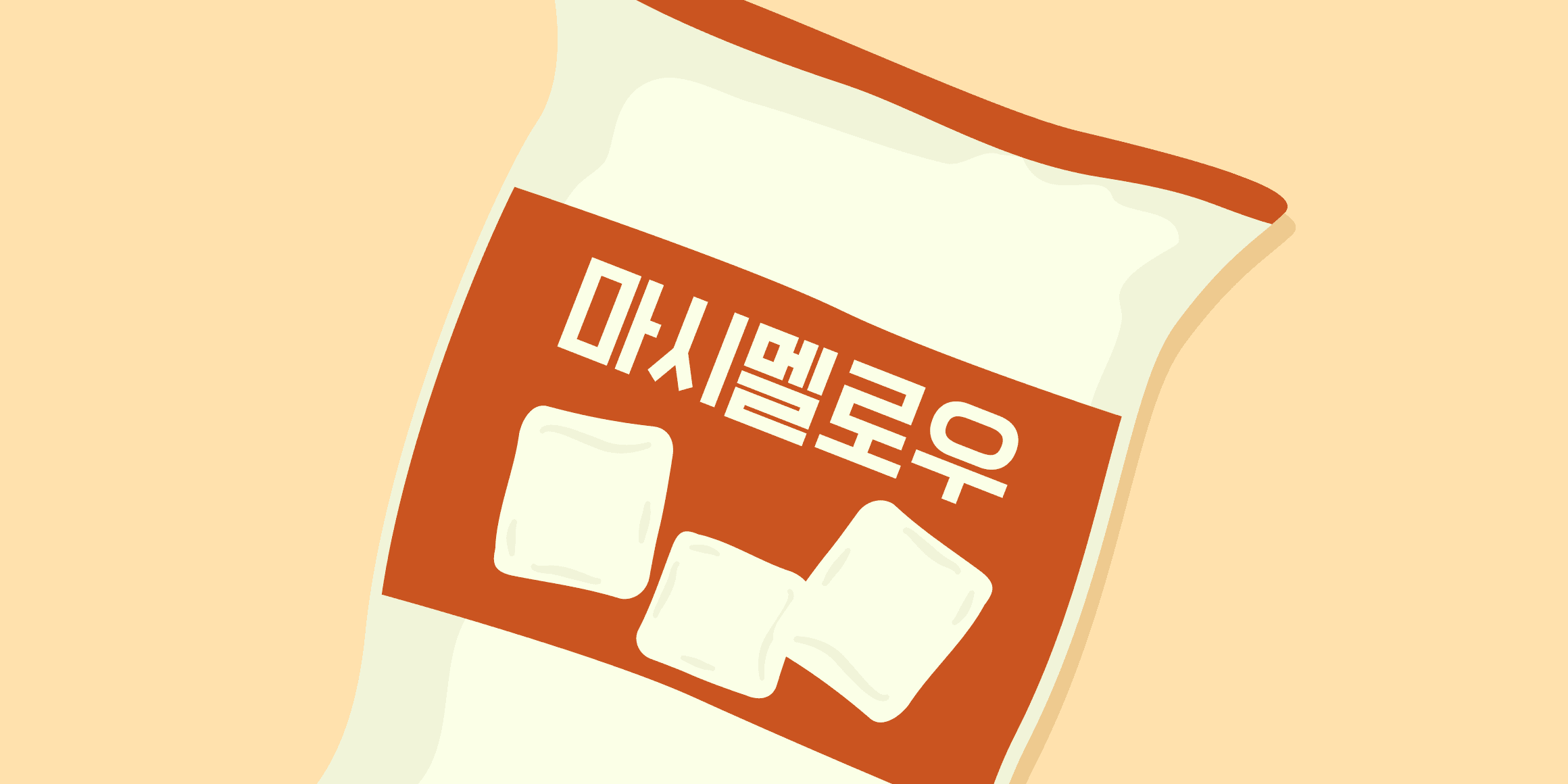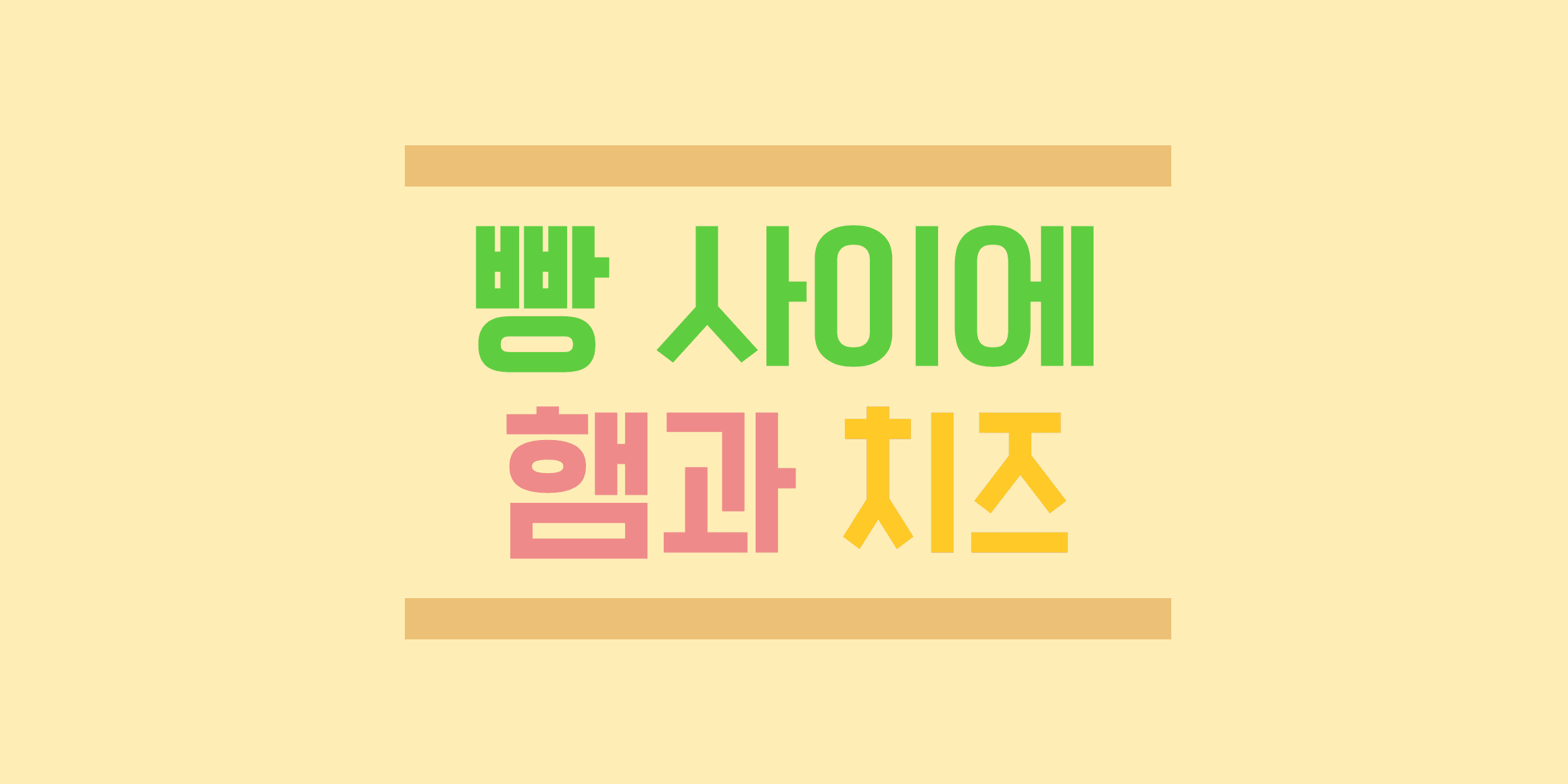
토스트
둥글고 부드러운 디스플레이 서체
둥글고 부드러운 획이 특징인 디스플레이 서체로, 따뜻하고 다정한 인상을 전달합니다. 카페 메뉴, 베이커리 로고, 키즈 브랜드 등에 사용하면 달콤하고 편안한 분위기를 연출하며, 자칫 밋밋해 보일 수 있는 레이아웃에 생동감을 더합니다. 획 끝이 라운드 처리되어 친근감을 높이며, 간결한 형태로 활용도가 높습니다.